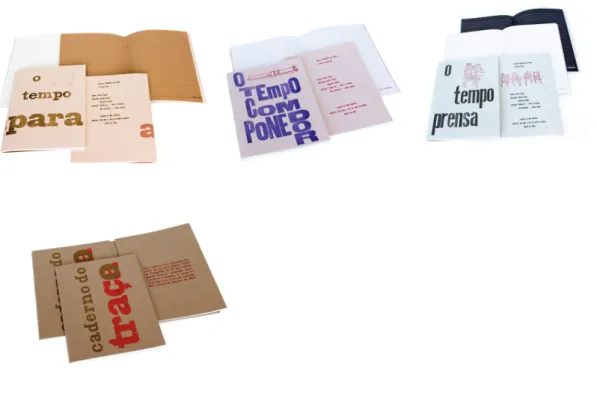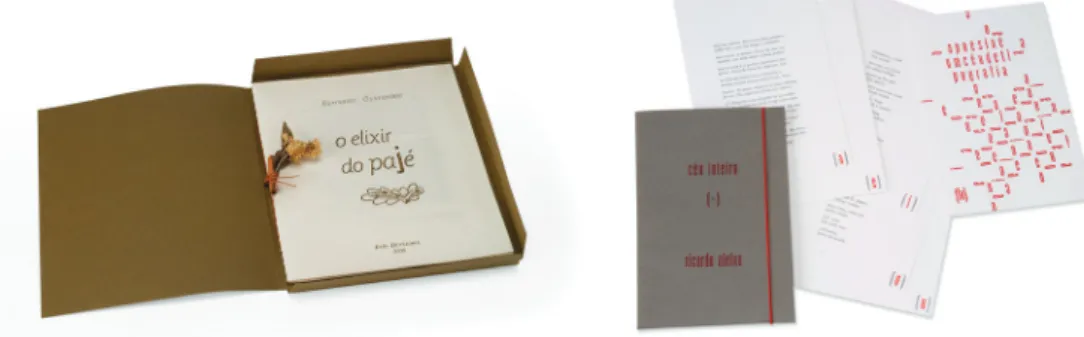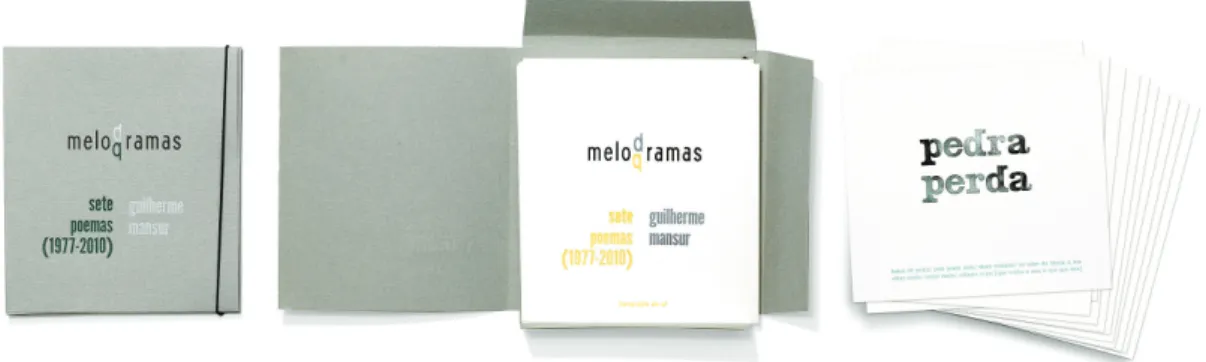
DOS LIVROS AOS TIPOS: UM INVENTÁRIO
GRÁFICO DA TIPOGRAFIA DO ZÉ
Este artigo tem como tema o resgate da impressão tipográfica na contemporaneidade pelo design gráfico brasileiro e como objeto a produção do designer Flavio Vignoli e da Tipografia do Zé. Buscou-se portanto, identificar e analisar as características da produção do designer, bem como discutir as motivações relacionadas ao seu envolvimento com a impressão tipográfica.
This work has as theme the letterpress printing revival on modern times in Brazilian Graphic Design and as object the production by the Designer Flavio Vignoli and “Tipografia do Zé” (Zé’s Letterpress Workshop). The research focused in to identify and
analyze the designer’s production characteristics, as well discuss the motives tied to his involvement with the letterpress process.
1 INTRODUÇÃO
Este texto é uma versão revista e ampliada de um excerto da dissertação “A prática contemporânea da impressão tipográfica no design gráfico brasileiro” desenvolvida no Programa de Pós– Graduação em Design da Universidade Anhembi-Morumbi no âmbito da linha de pesquisa “Design, Tecnologia e Linguagem”. A pesquisa como um todo analisa a produção de designers brasileiros que se utilizam da impressão tipográfica de modo a explorar as possibilidades expressivas daquela tecnologia. Dentro desse escopo destaca-se
a Tipografia do Zé, uma editora de livros artesanais formada pelo designer e professor Flavio Vignoli. O presente texto traça um breve histórico do percurso da Vignoli por considerá-lo parte importante e desconhecida da história recente do design gráfico mineiro e tece alguns comentários sobre a linguagem gráfica resultante de sua atividade.
O relato exposto neste artigo foi construído sobretudo por meio de entrevistas realizadas pelos autores, sendo que a natureza qualitativa e o caráter exploratório da investigação fez com que se optasse pela utilização da metodologia da História Oral para a coleta e análise dos dados. A História Oral pode ser entendida como “um procedimento metodológico” capaz de “registrar, através de narrativas induzidas e estimuladas, testemunhos, versões e interpretações sobre a História em suas múltiplas dimensões” (Delgado, 2010, p. 15). Dessa maneira foi possível registrar as diferentes visões individuais formalizando-as em documentos que por sua vez permitem identificar temas
relevantes a partir do entrecruzamento de informações. As entrevistas realizadas foram do tipo temática por serem mais adequadas para o registro de experiências e processos específicos vivenciados pelos depoentes. Os depoimentos foram registrados em vídeo acompanhado de um gravador de som. Posteriormente à gravação, passou-se ao processamento dos depoimentos. Como complemento, foram coletados dados em outras fontes primárias (documentos) e secundárias (livros e revistas). Assim, ao combinar esses diferentes procedimentos foi possível a elaboração desse relato.
A validade deste estudo se deve, em especial, à escasses de estudos que investigam a crescente valorização da incorporação de técnicas manuais e mecânicas ao projeto tipográfico, fenômeno perceptivel em diferetentes partes do mundo. Jury (2006) observa que o retraimento comercial da impressão tipográfica tem permitido nos últimos anos que designers e artistas gráficos interessados nas particularidades expressivas dessa tecnologia adquiram esses antigos equipamentos dando-lhes um novo fazer produtivo. Para Rocha (2011) o fato de muitos designers estarem voltando seu olhar e atenção para essas técnicas do passado, atesta a busca por uma materialidade que dificilmente pode ser emulada pela tecnologia digital. Drucker (1996) observa que pensar a materialidade do impresso gráfico evoca duas questões indissociáveis: a primeira é compreender a matéria em seu sentido literal, isto é, entender como a materialidade de um artefato é expressa pelos meios com os quais é feita, tornando-a assim tangível pelos nossos sentidos. A segunda é entendê-la como resultado de um processo cultural, como um registro das intenções, escolhas e valores de quem projetou o artefato.
2 A TIPOGRAFIA DO ZÉ
2.1 2.1 Do teatro para o design
Antes de se envolver com o design gráfico, Flávio Vignoli cursou direito na Universidade Federal de Minas Gerais (UFMG), área
que logo abandonou para se dedicar ao teatro profissional. Em seu depoimento, Flávio observa que o teatro foi uma grande escola e que, no ambiente cênico, desenvolveu as funções de ator, diretor artístico, cenógrafo e iluminador. Em paralelo à sua formação no palco e nas coxias, cursou, entre os anos de 1992 e 2001, Programação Visual na Universidade do Estado de Minas Gerais (UEMG). De seus anos na faculdade, recorda-se do descompasso entre a vivência acadêmica e a profissional, o que o levou a certa desmotivação que fez com que atrasasse o curso algumas vezes.
Com o tempo, Flávio direcionou sua carreira para o design gráfico, em especial para o design de exposições e o design editorial. Entre 2003 e 2004, enquanto trabalhava na Fundação Clóvis Salgado (FCS) como chefe do departamento de artes plásticas – sendo o responsável pelo projeto e montagem de exposições –, cursou a Especialização em Artes na Escola Guignard (UEMG) e, nesse mesmo período, começou
a lecionar na Universidade FUMEC – primeiramente em disciplinas no curso de Design de Interiores e, na sequência, no curso de Design Gráfico.
Segundo Flávio, o interesse pela impressão tipográfica surgiu nesse período de transição entre o teatro e o design. Leitor ávido, iniciou uma pequena – porém respeitosa – coleção de livros nos quais a qualidade do texto literário se somava à qualidade dos projetos gráficos. Dentre os diferentes itens de seu acervo, alguns se destacavam pelos aspectos táteis e materiais, livros tipográficos que refletiam uma qualidade que ele começou a perseguir em seus trabalhos profissionais. Dentre as obras de seu acervo destacam-se alguns títulos das editoras brasileiras Cattleya Alba, Dinamene, Noa Noa, O Livro Inconsútil, O Gráfico Amador, Philobiblion e Sociedade dos Cem Bibliófilos do Brasil. Outro passo importante em direção à impressão tipográfica aconteceu em 2005, já em seu próprio estúdio, quando participou conjuntamente com o professor Paulo da Terra Caldeira da curadoria da exposição de livros raros da Coleção Rita Adelaide, pertencentes ao acervo da Biblioteca Pública Estadual Luiz